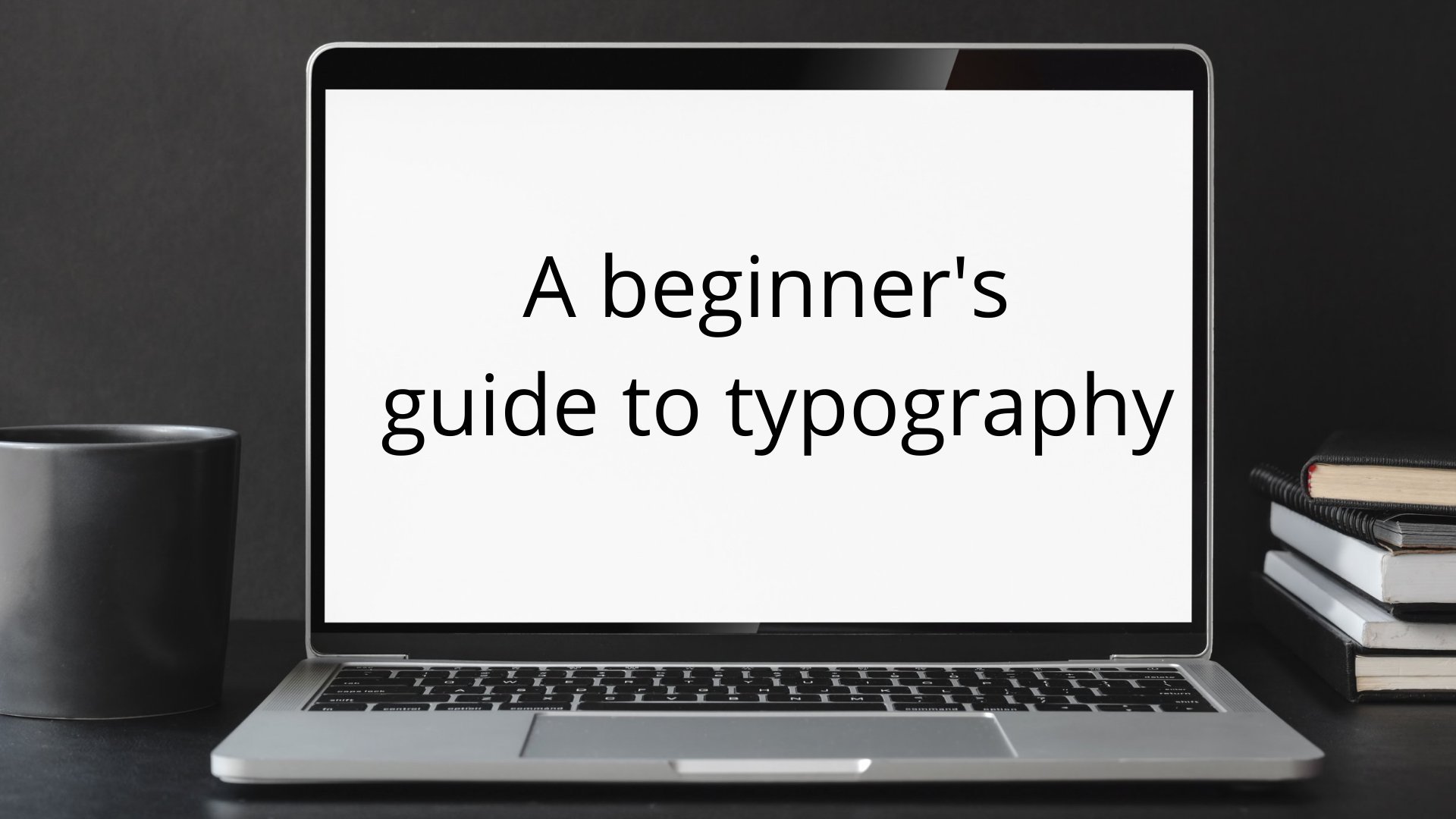
1. Introdução: Qualquer pessoa familiarizada com
marketing, design gráfico ou apresentação visual
de um produto em geral provavelmente está ciente
do que é topografia. Para aqueles de vocês completamente
novos que não sabem, topografia é definida
como a arte ou procedimento de organizar tipo ou processamento de dados
e treinamento a partir dele, ou o estilo e a aparência
da matéria impressa. Basicamente, significa que se
você está escrevendo algo, é como as letras parecem para os olhos, o
que soa trivial. Mas quando usado de forma inteligente, ele pode transmitir sutilmente
um certo sentimento para um público e
diferentes tipos de fontes, ou mais atraente para diferentes públicos
e mercados diferentes. Então este é o
guia para iniciantes para tipografia. Então, se você é alguém que é completamente novo na tipografia ou se você é alguém que já experimentou e
quer apenas rever o básico. Este curso é perfeito para você. Aqui aprendemos sobre os principais tipos básicos de
fonte e como usá-los, bem
como por que a
topografia é importante. E um único uso e mixagem de fontes e um
projeto de classe onde você
criará fontes para um
produto fictício para um novo público. Agora, com tudo isso
fora do caminho, vamos entrar na lição.
2. O que é tipografia: Agora, para o que é topografia, basicamente, o que ela
basicamente significa é que certos aspectos da fonte
significam coisas diferentes. Por exemplo, uma fonte
como essa tem uma sensação antiga muito clássica. Isso faz com que algo pareça
muito confiável em resistente. E nunca
sairá de moda. Algo assim. Parece elegante, moderno
e atualizado. Algo assim. Parece muito alto. Mais uma vez, ele apenas explica
uma barra muito alta. Algo assim,
atrai crianças. Também há aprendendo
a misturar fontes, bem
como aprender o que
coisas como negrito, fonte
itálica podem fazer. Se você quiser saber
o que cada um deles é para urina no lugar certo. Então, vamos continuar com o que
são chamados de fontes Serif.
3. de de Serifo: O primeiro tipo de fonte sobre o qual
falaremos é chamado de fontes Serif. Serif significa pé pequeno. E as serifas em fontes
serifas são aqueles pequenos traços quase que estão nas bordas de
letras como esta. Esse círculo
aqui é um serif. Serif são bastante clássicas. Eles mostram confiabilidade
e geralmente são bastante seguros e funcionam muito bem
com a palavra escrita. Então, se você estiver
digitando é algo que
seria impresso, como um livro ou uma revista. E jornal, ou
peça de marca em uma placa ou algo
que é vendido em uma loja. fontes Serif
funcionarão muito bem. Além disso, se o seu produto
estiver voltado para pessoas que estão um
pouco do lado mais antigo, fontes
serif no seu logotipo e outras marcas geralmente
serão muito atraentes para elas. Em seguida, falaremos
sobre as fontes San Serif.
4. Fontes de Sans: Em seguida, estão as fontes sans serif. As fontes Sans serif são
fontes sem as serifas, sem os pezinhos
nas bordas das palavras,
como esta. As fontes SAN-serif geralmente
parecem muito limpas, realmente modernas e muito elegantes, independentemente do
período de tempo, elas são usadas. Um logotipo com uma fonte sans serif
que foi feita há 30 anos ainda
parecerá
relativamente moderno hoje. Como resultado, as fontes San
Serif geralmente atraem um público mais jovem,
não necessariamente crianças, mas se os adultos mais jovens do seu
público-alvo, fontes
san-serif geralmente
funcionarão muito bem e são
provavelmente sua melhor aposta. Devido às fontes san serif também funcionam muito bem em uma tela. A maioria das coisas, como sites ou quaisquer artigos on-line
que devem ser lidos como PDFs, também funcionará muito
bem com uma fonte San Serif. Então, se você é uma empresa digital ou atraente para pessoas mais jovens, provavelmente sua melhor aposta
para ir com san serif.
5. Fontes de script: As fontes de script são
aquelas que se parecem escrita
cursiva, como esta. Uma fonte de script geralmente
faz com que algo pareça muito elegante ou high-end. Então, se sua empresa
está vendendo é algo muito caro, como um casamento, ou apenas algo mais voltado para ganhadores mais
altos. Uma fonte de script é provavelmente
o que você gostaria de usar.
6. Exibição de fontes: Fontes de exibição como essa geralmente são usadas
mais para títulos, outdoors
grandes e títulos. Eles não são recomendados
para nenhum corpo de texto. Então, o texto principal de um site, um livro e um jornal, qualquer coisa que geralmente
seria qualquer um dos outros três. Provavelmente não é uma boa
ideia para exibição, mas se você quiser
ter uma única palavra
destacada em algo
como um outdoor, as fontes de
exibição são
provavelmente sua melhor aposta. Apenas certifique-se de usá-los com muita
moderação porque eles são difíceis de ler e podem parecer um pouco estranhos
quando há um monte deles.
7. Bold, itálico, sublinha: Agora, para negrito, itálico e sublinhado, esses
três são frequentemente usados para
destacar certas palavras. Mas é muito importante que você tente não usar
esses três juntos. E, se possível, tente nunca usar dois
deles ao mesmo tempo. Negrito deve ser usado para títulos. E chamando
a atenção para palavras-chave, como algo assim. Mas se você usá-lo com muita frequência
, acabará com algo assim que é
muito difícil de ler. itálico geralmente pode ser usado para
destacar os nomes das pessoas. Sublinhados, novamente são usados para títulos e, muitas vezes, para hiperlinks. Se for algo online. Novamente, misturando demais
ou usando qualquer um desses, muitas vezes terão
o efeito inverso e diluem seu efeito ou
dificultam a leitura do texto. Por exemplo, veja esse
anúncio que é, isso não é bom. Algo assim
é muito melhor.
8. Mixagem de fonte: Agora, não tenha medo de
misturar determinadas fontes, como usar várias
fontes no mesmo logotipo. Isso é algo
que pode ser feito forma criativa, mas com cuidado ao
mesmo tempo. Agora, estou prestes a declarar algumas,
citações sem aspas, regras
para misturar fontes. Mas esteja ciente de que nenhuma
dessas são regras duras e
rápidas lá. Mais ainda, diretrizes como
tipografia é definitivamente mais uma arte do que uma
ciência delas
geralmente será mais
verdadeira do que não é verdadeira. Geralmente, você vai
querer combinar fontes que lhe dão o mesmo campo. Geralmente, por exemplo, fontes
muito divertidas que parecem um pouco semelhantes
farão um bom pai. Duas fontes que têm letras altas e
finas geralmente
combinam bem juntas. Mas as diferenças também são boas. Às vezes, combinar
uma fonte serif e sans serif pode funcionar lindamente. Se for esse o caso, a que você usa para letras
maiores deve ser aquela voltada para
seu público principal. A menos que seja um título
como este. Se você estivesse procurando
destacar a fonte serif, essa seria uma
boa maneira de emparelhá-la com uma fonte sans serif. E isso é o oposto. Isso também funciona para
nossas fontes de script , como visto em exemplos
como este. Agora, ao misturar fontes, é melhor tomar seu tempo
e usar tentativa e erro. Portanto, aproveite suas chances e sinta-se à vontade para
quebrar algumas delas, cite regras sem aspas
e experimente. Você pode encontrar duas fontes que funcionam bem juntas
que ninguém mais
encontrou e tornam seu logotipo realmente criativo
e atraente. E isso pode
levar a muito sucesso. E você terá a
oportunidade perfeita de fazer isso em nosso próximo projeto de classe.
9. Projeto do curso: Agora, para o nosso projeto de classe, quero que você crie um logotipo com as fontes
que você deseja. No entanto, usando a planilha
anexada, você explicará
seu uso de fontes e usará seu público-alvo, bem
como as regras que
declarei
nas lições anteriores para